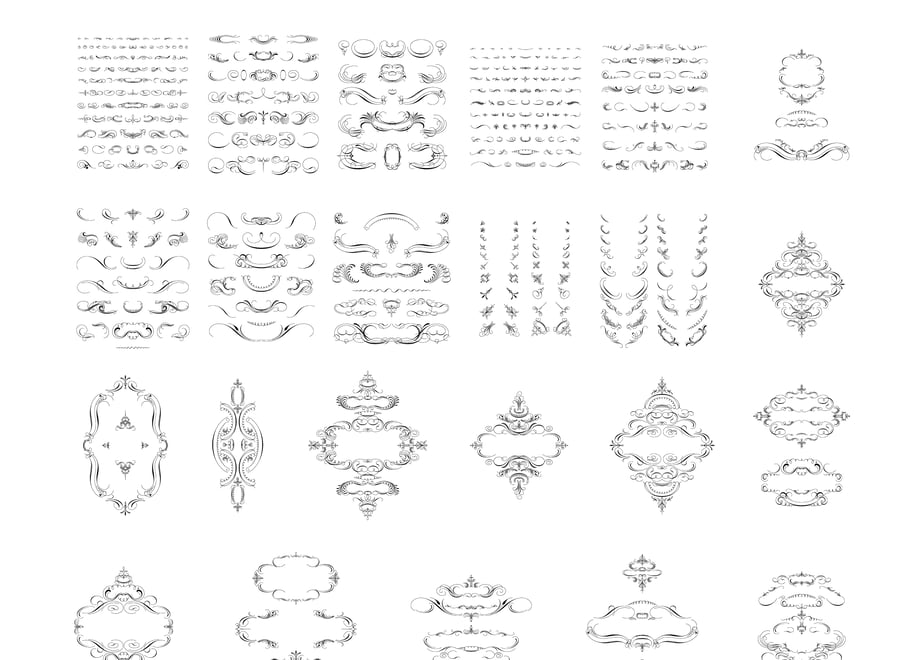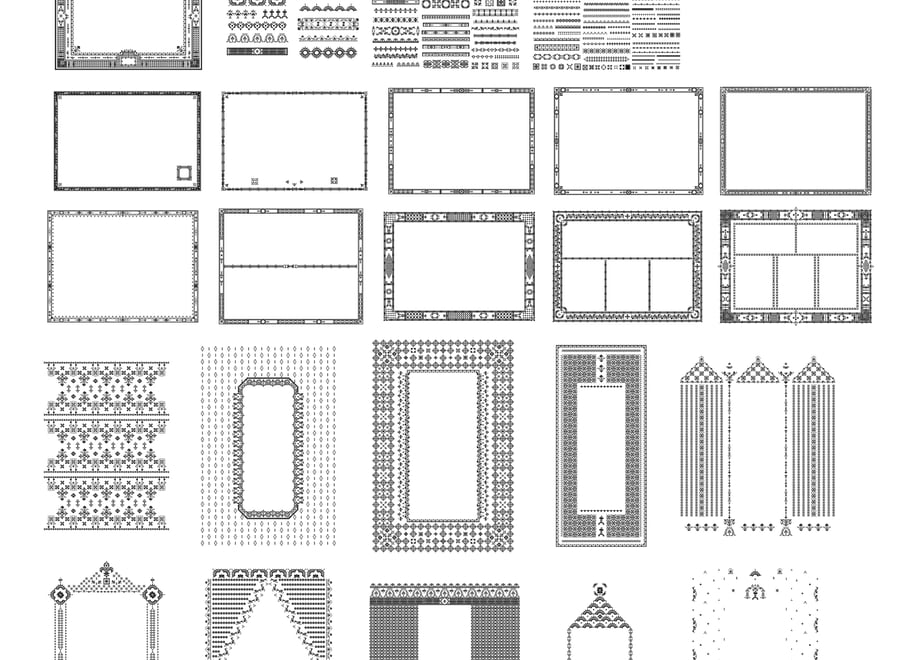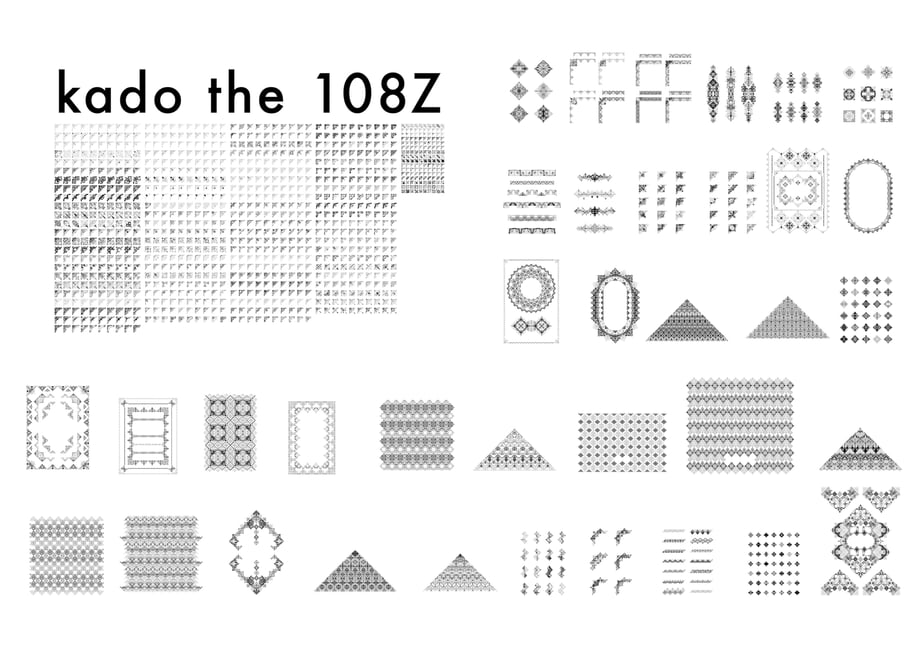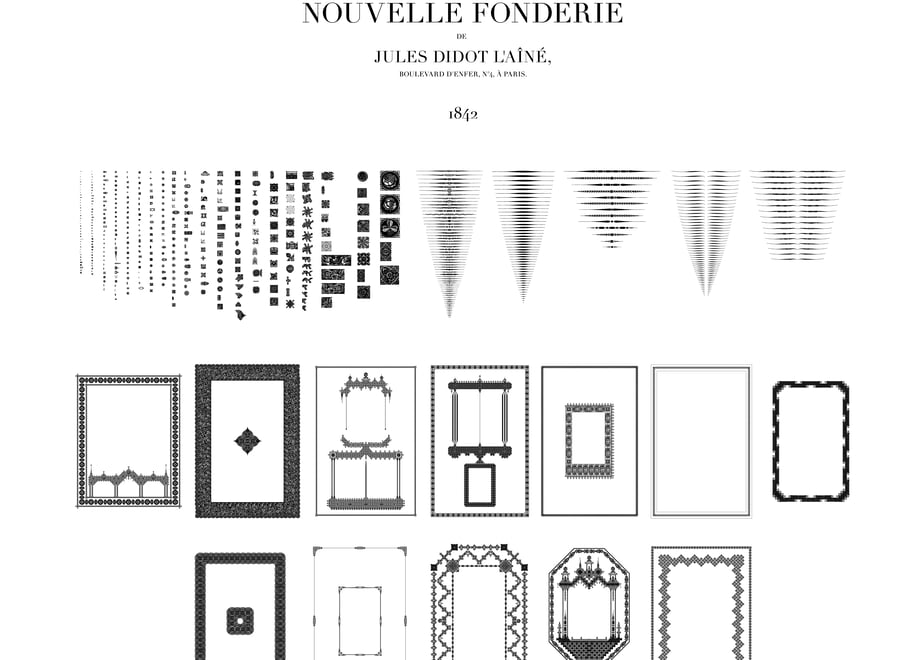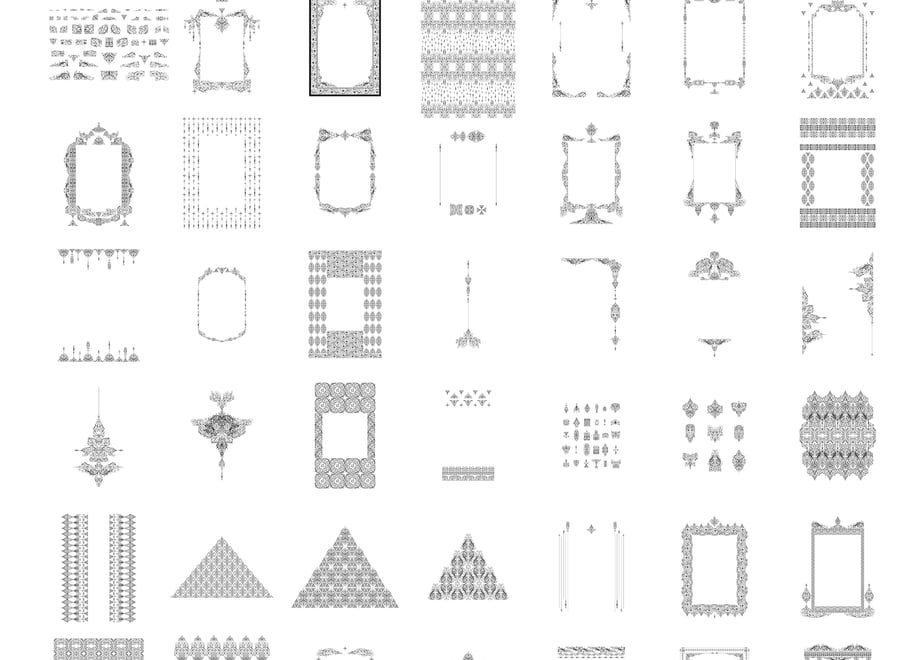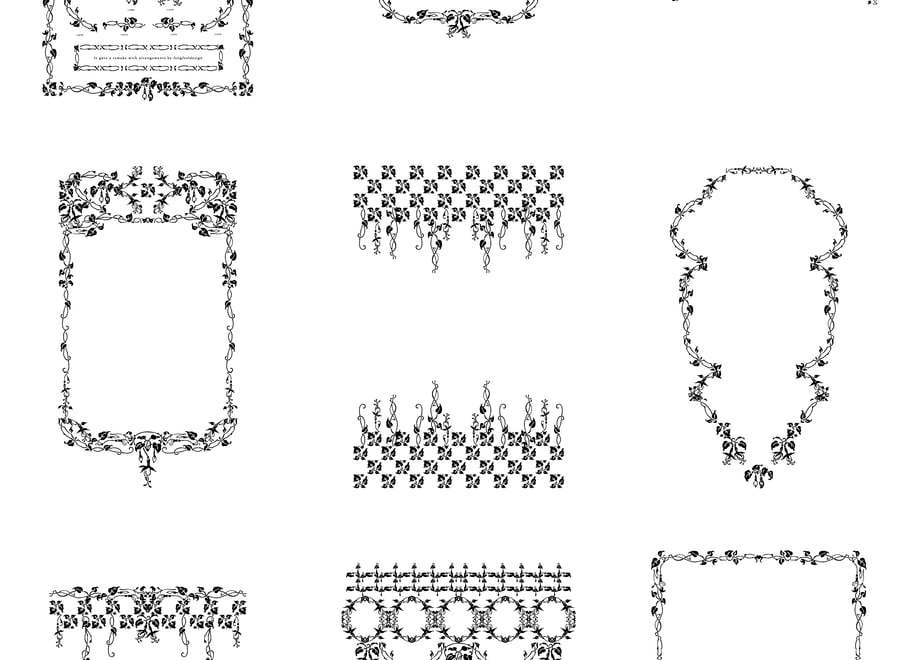
装飾活字:Lighthouse Type Foundry Complete Archive
歴史的な活字見本帳や印刷資料に収録された花形装飾活字をもとに、現代のデザイン環境で活用できるよう再構築したアーカイブコレクションです。
本商品は、Lighthouse Type Foundryで公開している歴史資料シリーズを1つにまとめたコンプリートエディションとなります。
収録内容
・装飾オブジェクト 2,188種
・装飾罫線 190種
・組見本 139種
PRINTERS' FLOWERS joh. enschede en zoen te haarlem
オランダの印刷文化を伝える歴史資料に収録された花形装飾活字コレクション。
54種類の装飾オブジェクトと41種類の組見本を収録。
Modeles des caracteres de l'imprimerie et des autres choses necessaires audit art
18世紀フランスの活字見本帳に収録された装飾活字コレクション。
192種類の装飾オブジェクトと21種類の組見本を収録。
BORDURE FUCHSIA F
装飾罫線を中心に収録したデザイン資料。
38種類の装飾オブジェクトと8種類の組見本を収録。
SPÉCIMEN DE LA NOUVELLE FONDERIE DE JULES DIDOT L'AÎNÉ, BOULEVARD D'ENFER, N°4, À PARIS. 1842
フランスの活字鋳造所 Jules Didot による1842年の活字見本帳から採録した装飾活字コレクション。
403種類の装飾オブジェクト、190種類の装飾罫線、12種類の組見本を収録。
kado the 108Z
歴史的な角飾りを中心に再構成したコレクション。
1,080種類の装飾オブジェクトと36種類の組見本を収録。
Gravure et Fonderie C. Derriey. Specimen-album. [TRAITS DE PLUME]
ペンワークによる装飾図案や罫線を収録した歴史資料コレクション。
421種類の装飾オブジェクトと21種類の組見本を収録。